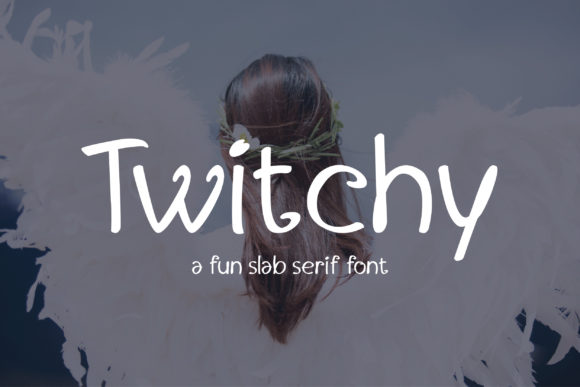
Twitchy - это причудливый шрифт с непринужденной тематикой, отличающийся прекрасным стилем.
Независимо от темы, этот шрифт будет невероятно полезен в вашей библиотеке шрифтов, поскольку он способен приподнять любое творение.